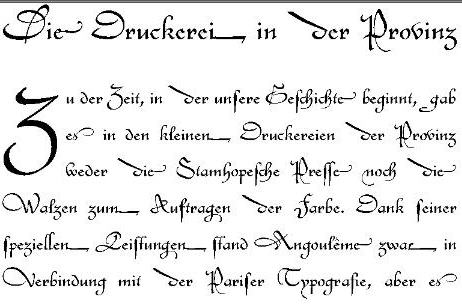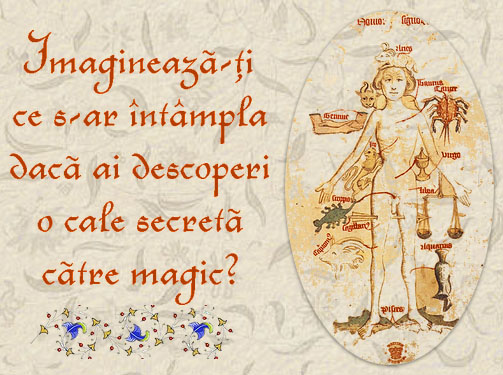
Lange Zeit eine meiner Lieblingsschriften - die französische Civilité.
Hier der Versuch, aus den alten Lettern eine auch heute brauchbare und lesbare Schrift zu erstellen. Der Font enthält eine Reihe von Schmuckzeichen und alternative Buchstabenformen, für die auf Wusch ein spezielles kleines Plug-In für Winword erhältlich ist, um damit die Ligaturen und Schmuckzeichen automatisch zu setzen.
Die Schnitte der einzelnen Lettern sind jenen der französischen "Lettre de Civilité"
nachgebildet und lehnen sich weitgehend an die Entwürfe der Fonderie Peignot (ca. 1580), von Fournier (1742) und die Form einzelner Versalen ist der Biblia Poliglotto vom Christoph Plantin (ca. 1570) entnommen.For a long time Civilité has been one of my favorite Fonts - this is the result of about 6 years of work with these types.
This font tries to provide readable letters that still show the charme of the old historic signs.
The cut of the letters is mainly taken from prints of the Fonderie Peignot, 1580, the work of Fournier, 1742, and some of the capitals may be found in the Biblia Poliglotto of Chrisoph Plantin, 1570.
Hier ein Beispiel für die Anwendung der vielen Sonder- und Endungszeichen, sowie der alternativen Buchstaben - hier D, d, n, g, s
In der aktuellen Version 6 dieser Schrift sind neben den üblichen deutschen und französischen Sonderzeichen eine ganze Reihe alternativer Buchstabenformen und Schmuckzeichen, wie Endungen und Ligaturen enthalten, siehe Typenliste. Here the actual design as of Nov. 2006. The font contains letters for german an french laguage, various alternates, special endings and ligatures